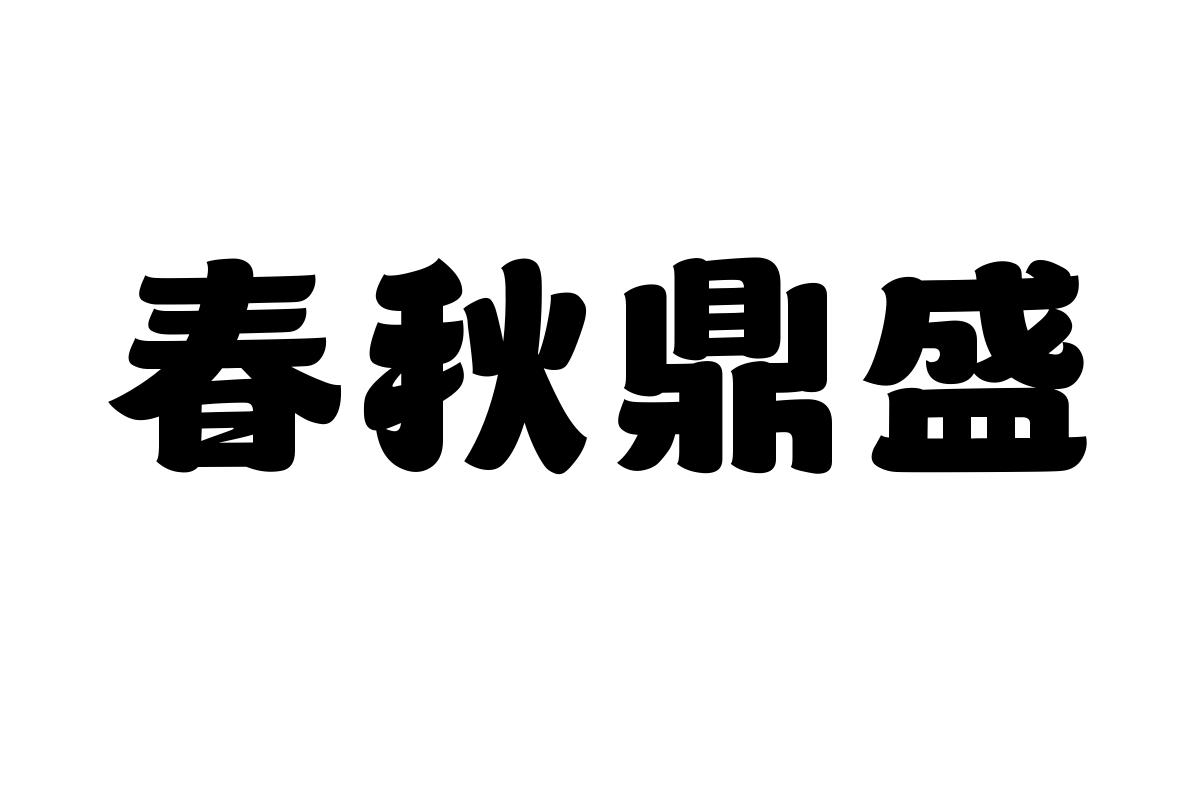
山海青云体是一套具有现代感和艺术风格的字体,它由设计师精心制作而成。这套字体的特点在于其独特的字形结构,使得它在视觉上显得非常独特和引人注目。
首先,山海青云体的笔画流畅而有力,给人一种强烈的视觉冲击力。它的每一个笔画都充满了力量和动感,仿佛在诉说着一个关于山、海、云的故事。这种独特的设计使得它在各种设计作品中都非常受欢迎。
其次,山海青云体的结构紧凑而富有层次感。它的每个字都是由多个部分组成的,这些部分相互交织在一起,形成了一种独特的视觉效果。这种结构使得它在视觉上非常吸引人,同时也使得它在排版设计中更加灵活和多变。
最后,山海青云体的字体风格独特,具有很强的个性。它不同于传统的中文字体,而是采用了一种全新的设计理念,使得它在视觉上非常独特和引人注目。这种独特的设计使得它在各种设计作品中都能够脱颖而出,展现出自己的独特魅力。
总的来说,山海青云体是一款非常优秀的字体,它的独特设计和强大的视觉冲击力使得它在各种设计作品中都能够展现出自己的魅力。无论是用于广告设计、网页设计还是其他任何需要文字的地方,山海青云体都是一个非常好的选择。